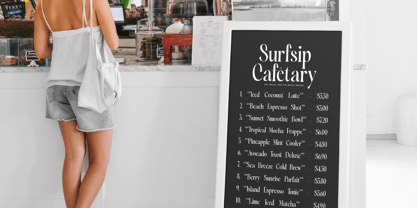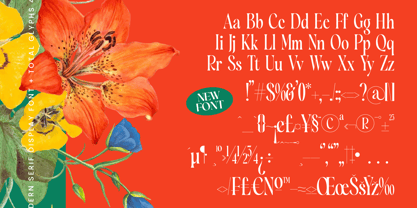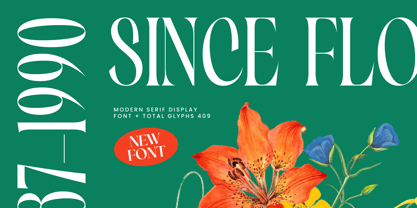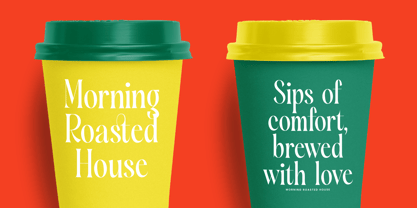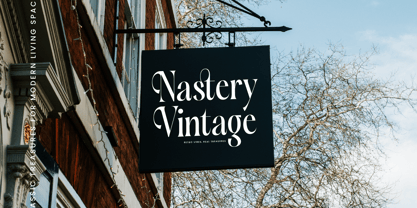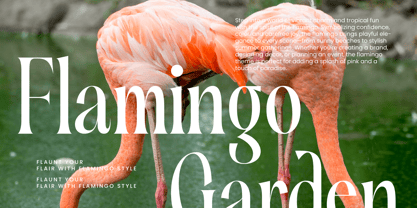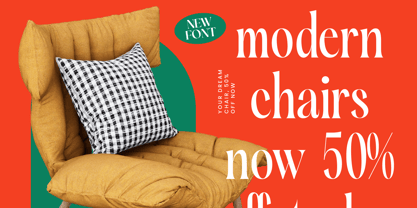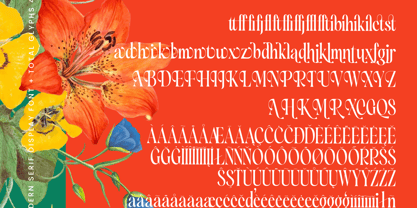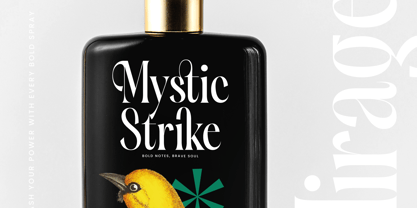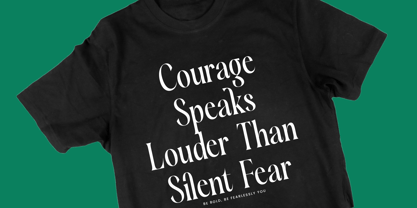
Silent Gingers
La familia tipográfica Silent Gingers fue diseñada por Heru Utama Putra y publicada por Timelesstype Studio. Silent Gingers contiene 2 estilos y opciones de paquete familiar.
Silent Gingers - Modern Serif Display , from Timelesstype, Suitable for any projects such as: logos, branding projects, homeware designs, product packaging, mugs, quotes, posters, shopping bags, t-shirts, book covers, name card, invitation cards, greeting cards, label, photography, watermark, special events, and all your other luxury and beautiful projects that need a Luxury Serif taste.